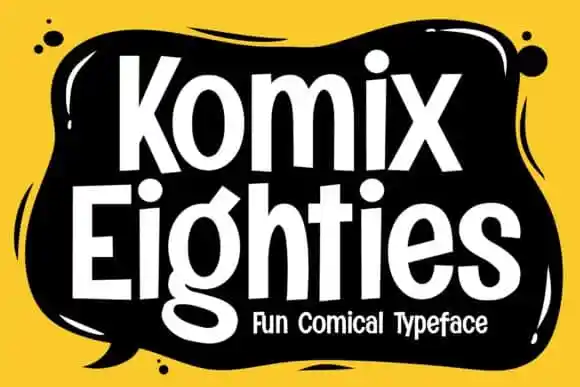
Komix Eighties Display Font – Download Grátis
A Komix Eighties Display Font é uma escolha perfeita para quem busca um estilo clássico contemporâneo. Seu design elegante ainda mantém sua influência calligrafica, mas ao mesmo tempo apela à modernidade e frescura. Perfeito para marcas de roupas t-shirt, logotipos, citações tipográficas, embalagens, headlines em blogs ou qualquer aplicação visual que exija uma aparição chamativa. A Komix Eighties Display Font não é apenas um recurso gráfico versátil, ela também atende a um amplo espectro de ideias criativas. De cartões de correspondência e títulos, até papelaria e embalagens – sua simplicidade perfeita oferece o aspecto que seu projeto necessita para transmitir impacto visual.